Что такое моноширинный шрифт и почему знаки равны по ширине
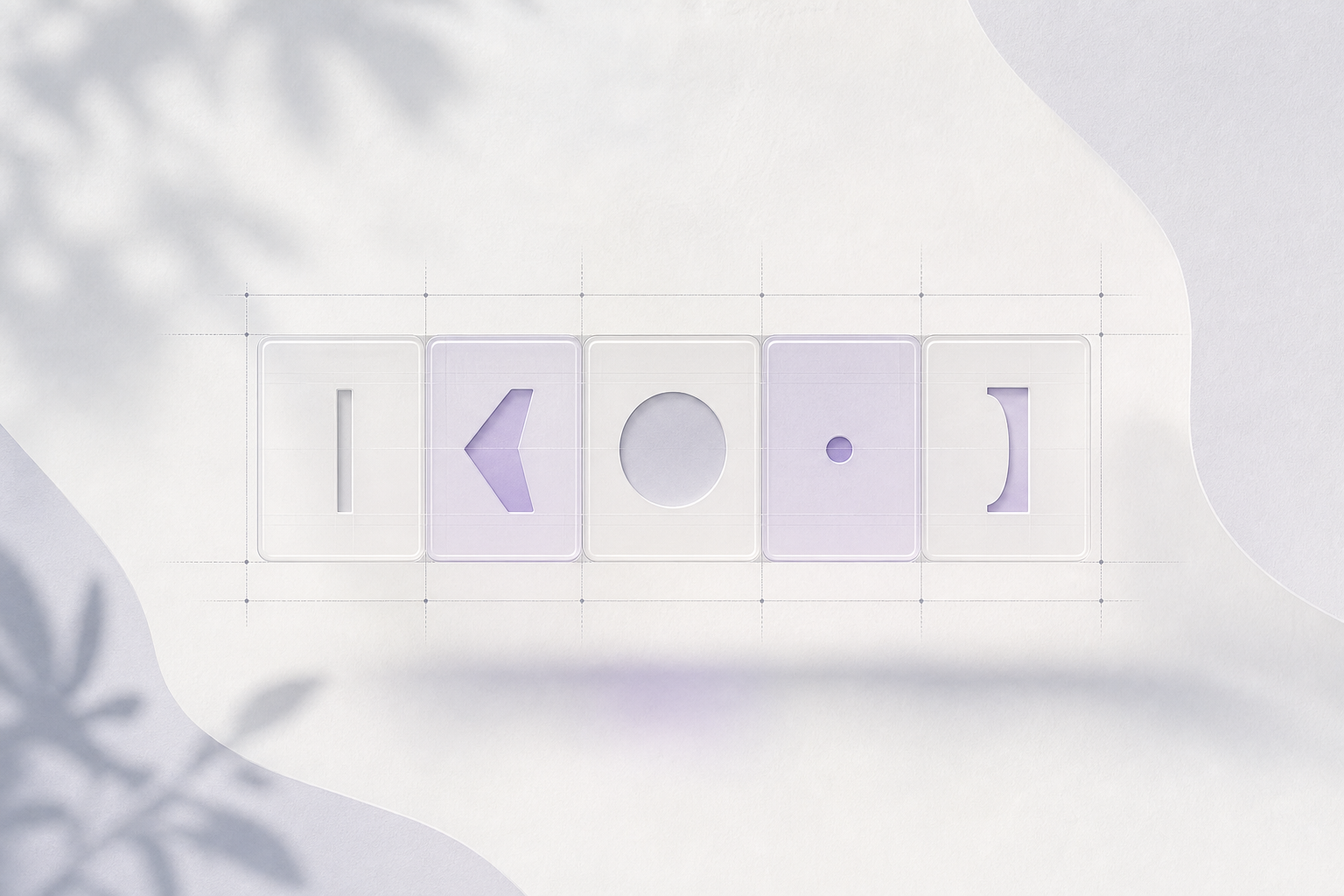
Что такое моноширинный шрифт и почему знаки равны по ширине
Моноширинный шрифт — это гарнитура, в которой каждому символу отведена одинаковая горизонтальная ширина, независимо от формы буквы или знака. Поэтому узкая «i» занимает столько же места, сколько широкая «M». Такой принцип удобен для кода, таблиц и текстовых интерфейсов, где важны ровные колонки и предсказуемое выравнивание.
Как устроен шрифт с одинаковой шириной символов
В любом шрифте символ располагается внутри условной прямоугольной области, которую называют знакоместом. В моноширинной гарнитуре ширина этого знакоместа одинакова для букв, цифр, пробела и большинства знаков препинания. Рисунок символа может быть уже или шире, но границы его колонки остаются постоянными.
Равная ширина не означает, что все знаки визуально выглядят одинаковыми по размеру. Буква «I» может занимать узкую часть своей колонки, а «W» — почти всю колонку. Между контуром и краями знакоместа остаётся свободное пространство, поэтому набор сохраняет общий шаг, но не превращается в ряд одинаковых прямоугольников.
У моноширинного шрифта есть важная техническая особенность: его ширина измеряется не для каждого символа отдельно, а как единый шаг строки. Это позволяет заранее понимать, где окажется каждый следующий знак. В терминале, редакторе кода или ASCII-графике такое поведение полезнее индивидуальной настройки расстояний между буквами.
Моноширинный и пропорциональный шрифт: в чём разница
Пропорциональный шрифт задаёт символам разную ширину в зависимости от их формы. Узкие знаки занимают меньше места, широкие — больше, а расстояния между буквами подбираются так, чтобы слова выглядели компактно и ритмично. Такой подход обычно лучше подходит для больших объёмов обычного текста, потому что строка получается плотнее и естественнее для чтения.
Моноширинная гарнитура жертвует компактностью ради геометрической регулярности. Строка из десяти символов занимает столько же места, как любая другая строка из десяти символов при тех же настройках. Это делает простым вертикальное выравнивание, подсчёт позиций и сравнение фрагментов текста.
- Моноширинный шрифт использует один шаг для всех символов.
- Пропорциональный шрифт использует индивидуальную ширину знаков.
- Моноширинная гарнитура упрощает выравнивание по колонкам.
- Пропорциональная гарнитура обычно экономит место и лучше подходит для книжного набора.
- Выбор зависит от задачи, размера текста и требуемой точности позиционирования.
Почему одинаковая ширина важна для кода и терминала
В программном коде отступы и вертикальное выравнивание помогают быстро распознавать структуру. Если пробелы, скобки и символы имеют предсказуемый шаг, блоки кода образуют ровные визуальные колонки. Разработчик легче замечает вложенность, сопоставляет открывающие и закрывающие элементы, сравнивает две версии файла и читает сообщения командной строки.
Например, в моноширинном начертании два списка могут визуально совпасть по разделителям: имя переменной, знак равенства и значение будут стоять в одинаковых позициях. В пропорциональной гарнитуре длинное имя сдвинет последующие элементы, и для выравнивания понадобятся дополнительные пробелы или специальное форматирование.
Терминальные интерфейсы также используют фиксированный шаг сетки. Команды, пути к файлам, журналы событий и системные сообщения часто выводятся строками, где положение символа имеет значение. Благодаря одинаковой ширине текстовый интерфейс может показывать простые рамки, меню и таблицы без сложной графической вёрстки.
Практический пример выравнивания
Представьте список расходов: «Кофе 120», «Обед 450» и «Такси 780». В моноширинном шрифте цифры можно расположить по одной вертикальной колонке, добавив одинаковое количество пробелов. В пропорциональном начертании ширина букв различается, поэтому визуальное выравнивание становится менее надёжным и зависит от конкретной гарнитуры.
Где ещё применяют монопространственные гарнитуры
Моноширинные шрифты применяют не только разработчики. Они подходят для документов, где важна сетка символов: текстовых макетов, технических спецификаций, логов, команд, шаблонов данных и некоторых видов форм. Их также используют в визуальной айдентике, постерах и интерфейсах, когда нужно подчеркнуть технологичность, системность или связь с ранней компьютерной эстетикой.
В дизайне моноширинная гарнитура может работать как акцентный шрифт. Ею выделяют подписи, номера, метки, навигационные элементы и короткие технические сведения. Для длинного маркетингового текста такой выбор требует осторожности: одинаковая ширина увеличивает длину строк и может сделать чтение более медленным.
- Кодовые редакторы и интегрированные среды разработки.
- Терминалы, консоли и журналы системных событий.
- Текстовые таблицы и данные с фиксированными колонками.
- Техническая документация и примеры команд.
- Постеры, интерфейсы и брендинг с технологическим характером.
- Макеты, где нужно визуально показать координатную сетку символов.
Какие характеристики проверить перед выбором шрифта
Одинаковая ширина — базовое свойство, но не единственный критерий качества. Для кириллического текста важно проверить, есть ли в гарнитуре полноценный набор русских букв, корректные формы знаков препинания и различимые символы, например «О» и ноль, «l» и единицу, «I» и заглавную «i» в латинице. Чем дольше чтение, тем важнее эти детали.
Оцените также размер x-height, контраст штрихов, форму кавычек, скобок и математических знаков. В коде особенно полезны выразительные различия между похожими символами и хорошо заметные знаки пунктуации. Для интерфейса дополнительно проверьте начертания, межстрочный интервал и поведение шрифта на небольшом экране.
- Определите задачу: код, таблица, интерфейс, документ или декоративный макет.
- Проверьте поддержку нужных алфавитов, цифр и специальных символов.
- Сравните похожие знаки: ноль, букву O, единицу, I, l и вертикальную черту.
- Оцените читаемость на реальном размере, а не только в крупном образце.
- Проверьте доступные начертания и лицензионные условия.
- Убедитесь, что шрифт корректно отображается в нужной программе или браузере.
Как использовать моноширинный шрифт в веб-дизайне
В веб-интерфейсе моноширинный шрифт лучше назначать конкретным компонентам, а не всей странице без необходимости. Он уместен для блоков кода, коротких идентификаторов, команд, времени, номеров версий и табличных значений. Основной пользовательский текст чаще оставляют пропорциональным, чтобы сохранить привычный ритм чтения и не увеличивать ширину контентной области.
Размер и межстрочный интервал нужно оценивать вместе с длиной строки. Если символы крупные, а колонка узкая, текст начнёт чаще переноситься. Если интервал слишком мал, строки визуально сливаются; если слишком велик, код и таблицы теряют компактность. Проверяйте не только латиницу, но и реальные русские подписи, цифры и знаки.
Частые ошибки при работе с моноширинными шрифтами
Первая ошибка — считать моноширинный шрифт универсальным. Его регулярность полезна для данных и кода, но не автоматически улучшает любой дизайн. Вторая — проверять только английский текст. Гарнитура может выглядеть аккуратно в латинице, но иметь неудачные кириллические формы, слишком тесные знаки или отсутствующие символы.
Третья ошибка — выравнивать текст большим количеством пробелов в пропорциональном шрифте. Такое решение ломается при смене гарнитуры, размера, масштаба или устройства. Если колонкам действительно нужен фиксированный шаг, используйте моноширинную гарнитуру либо структурные средства вёрстки, а не случайный набор пробелов.
Четвёртая ошибка — игнорировать контраст и фон. Тонкие штрихи на слабом контрасте плохо читаются независимо от ширины символов. Пятая — выбирать декоративное начертание для больших объёмов кода. Сначала проверяйте ясность форм, различимость знаков и стабильность отображения, а уже затем оценивайте характер и визуальный стиль.
Чеклист перед публикацией макета или интерфейса
- Проверьте, что каждый символ действительно занимает одинаковый шаг.
- Протестируйте кириллицу, латиницу, цифры и специальные знаки.
- Сравните ноль, букву O, единицу, I и строчную l.
- Убедитесь, что таблицы и отступы сохраняют выравнивание.
- Проверьте читаемость на основном размере и на мобильном экране.
- Оцените контраст текста и фона.
- Используйте моноширинный шрифт только там, где его свойство помогает задаче.
- Проверьте лицензию и наличие нужных файлов начертаний.
Что значит «моноширинный шрифт» простыми словами?
Это шрифт, в котором каждой букве, цифре и знаку отводится одинаковая ширина. Узкий символ не занимает меньше места, чем широкий. Благодаря единому шагу строки легко выравнивать по колонкам, показывать код и строить простые текстовые таблицы.
Почему программисты используют моноширинные шрифты?
Фиксированная ширина помогает видеть отступы, вертикальные колонки и структуру кода. Она также упрощает сравнение строк, чтение терминальных сообщений и отображение символов, положение которых важно. При этом конкретную гарнитуру выбирают ещё и по читаемости, поддержке языков и различимости похожих знаков.
Подходит ли шрифт одинаковой ширины для обычного текста?
Подходит, если нужен технический или стилистический эффект, но для длинных статей он не всегда оптимален. Все символы занимают одинаковое место, поэтому строки могут стать длиннее, а текст — плотнее или медленнее для чтения. Перед выбором проверьте реальный объём, размер и ширину колонки.
Чем монопространственный шрифт отличается от пропорционального?
Монопространственный, или моноширинный, шрифт использует одинаковую ширину знакоместа для всех символов. Пропорциональная гарнитура назначает каждому знаку собственную ширину. Поэтому пропорциональный текст обычно занимает меньше места, а моноширинный лучше сохраняет геометрическое выравнивание.
Можно ли использовать моноширинный шрифт для кириллицы?
Да, если выбранная гарнитура содержит кириллический набор. Проверяйте не только наличие русских букв, но и качество их форм, знаков препинания, кавычек и тире. Образец нужно тестировать на фразах, которые будут использоваться в макете, поскольку латиница не показывает всех особенностей кириллицы.
Почему ноль и буква O должны различаться в шрифте для кода?
В программном коде ноль и буква O могут встречаться рядом, но обозначают разные символы. Если их форма почти совпадает, возрастает риск ошибки при чтении и наборе. Хорошие шрифты для кода делают различия заметными с помощью формы, внутренней отметки или других визуальных деталей.
Можно ли сделать собственный моноширинный шрифт?
Да. При проектировании нужно задать единый горизонтальный шаг, согласовать ширину всех знаков и проверить интервалы, метрики, кириллицу, цифры и специальные символы. Удобнее начинать с набора знаков, которые нужны для конкретной задачи, а затем расширять семейство и тестировать его в реальном тексте.
Вывод: когда выбирать шрифт с фиксированной шириной
Моноширинный шрифт делает ширину знаков предсказуемой: каждая буква, цифра и пунктуационный символ получает одинаковое знакоместо. Это особенно важно для кода, терминалов, таблиц и технических интерфейсов. Для длинного текста и спокойной типографики чаще выбирают пропорциональную гарнитуру, но окончательное решение зависит от задачи и тестового набора.